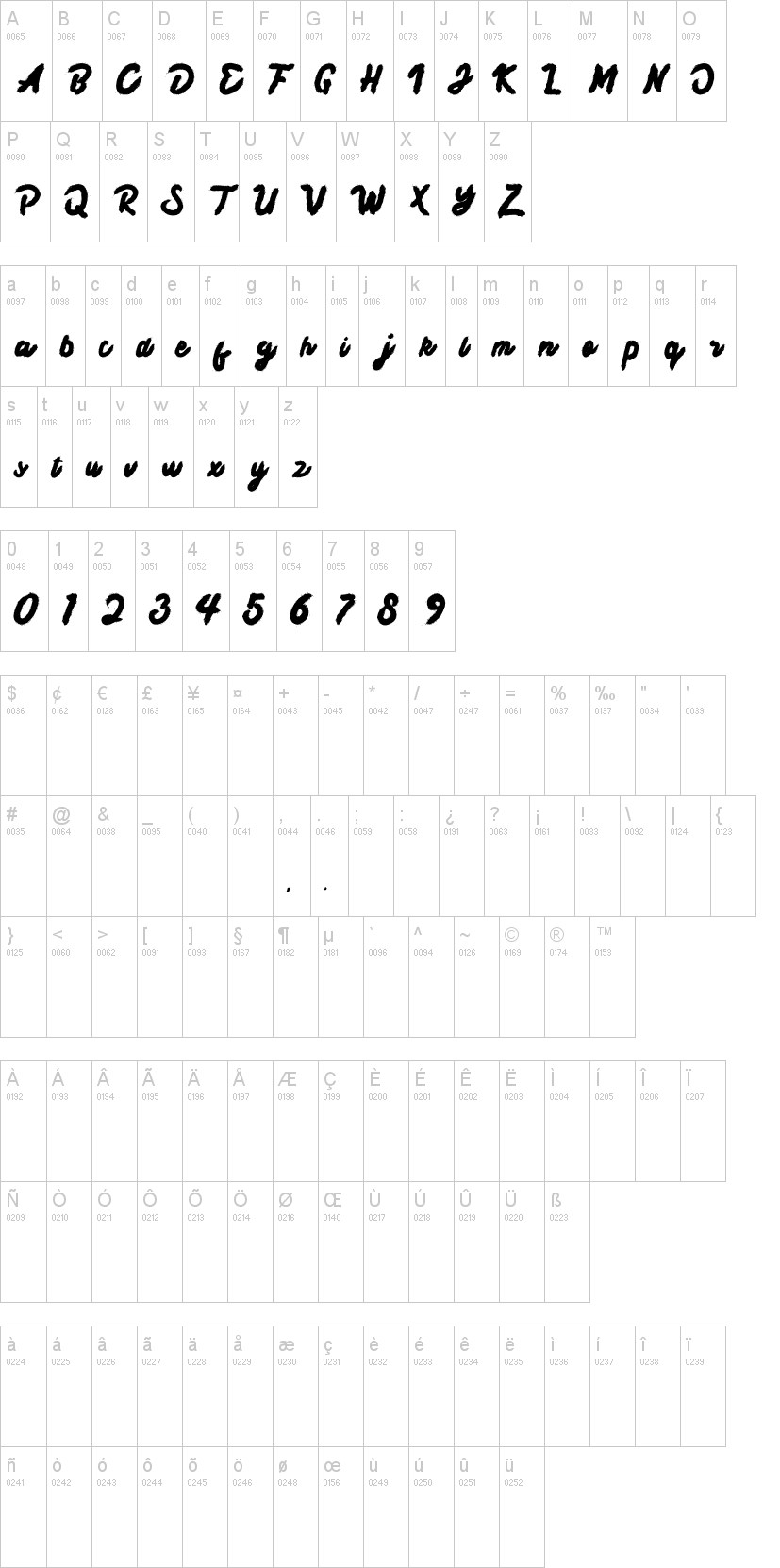
Taifun Script
Taifun Script 是一种手写字体,它的设计风格类似于毛笔书法,带有一定的艺术感和流畅感。它的笔画流畅、自然,形态优美,非常适合用于文艺、时尚、花艺、手工制作等领域。Taifun Script 字体包含了许多特殊字符,包括各种符号、数字和字母,可以满足不同领域和场景的需求。此外,Taifun Script 字体的制作工艺非常高端,具有卓越的印刷效果和阅读体验,是一种非常优秀的字体设计作品。
Taifun Script是一款非常不错的手写艺术字体,具有很好的视觉感,适合于文化类的宣传设计、商业类品牌的广告和产品包装设计以及个性化文字排版等较多场景。
Taifun Script字符映射图